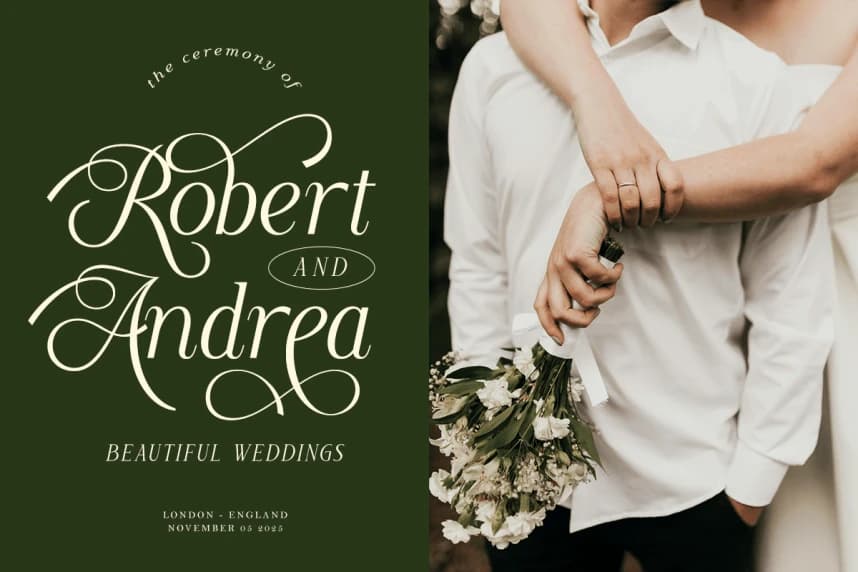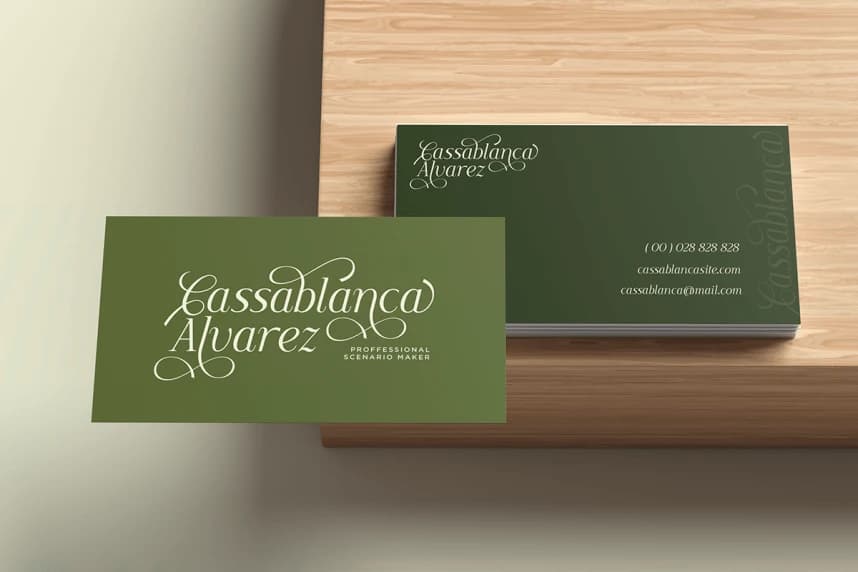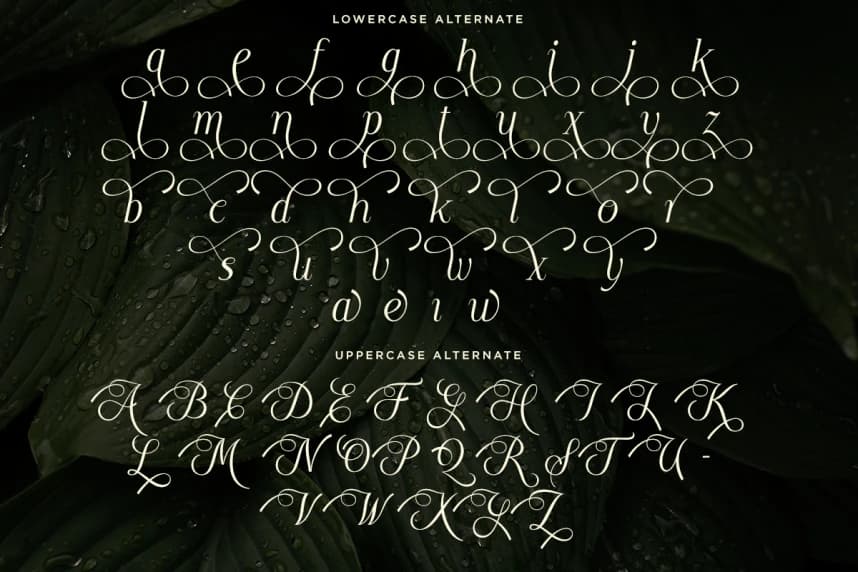
Moelania DEMO Font
Moelania DEMO Font, şık alternatiflere sahip lüks ve zarif bir italik yazı tipidir. Markalaşma, logolar, alıntılar ve posterler için mükemmeldir ve ayrıca düğün davetiyeleri için de idealdir. Bu font, çarpıcı ve sofistike tasarımlar yaratmanıza olanak tanır. Moelania ayrıca birden çok dili destekler
Moelania DEMO Font, şık alternatiflere sahip lüks ve zarif bir italik yazı tipidir. Markalaşma, logolar, alıntılar ve afişler için mükemmeldir ve ayrıca düğün davetiyeleri için de idealdir. Bu yazı tipi, çarpıcı ve sofistike tasarımlar yaratmanıza olanak tanır. Moelania ayrıca birden çok dili destekler.